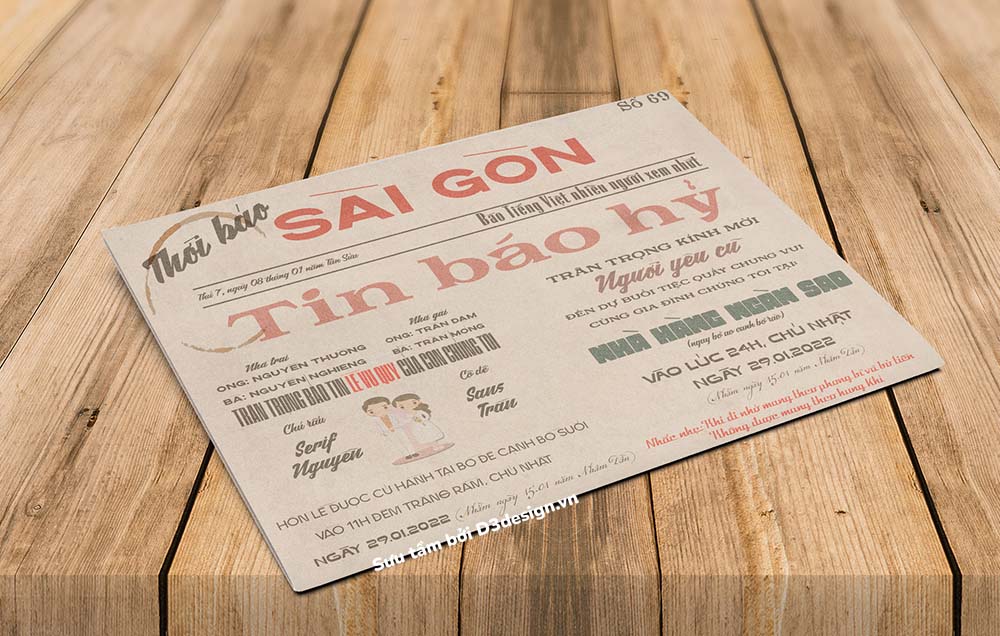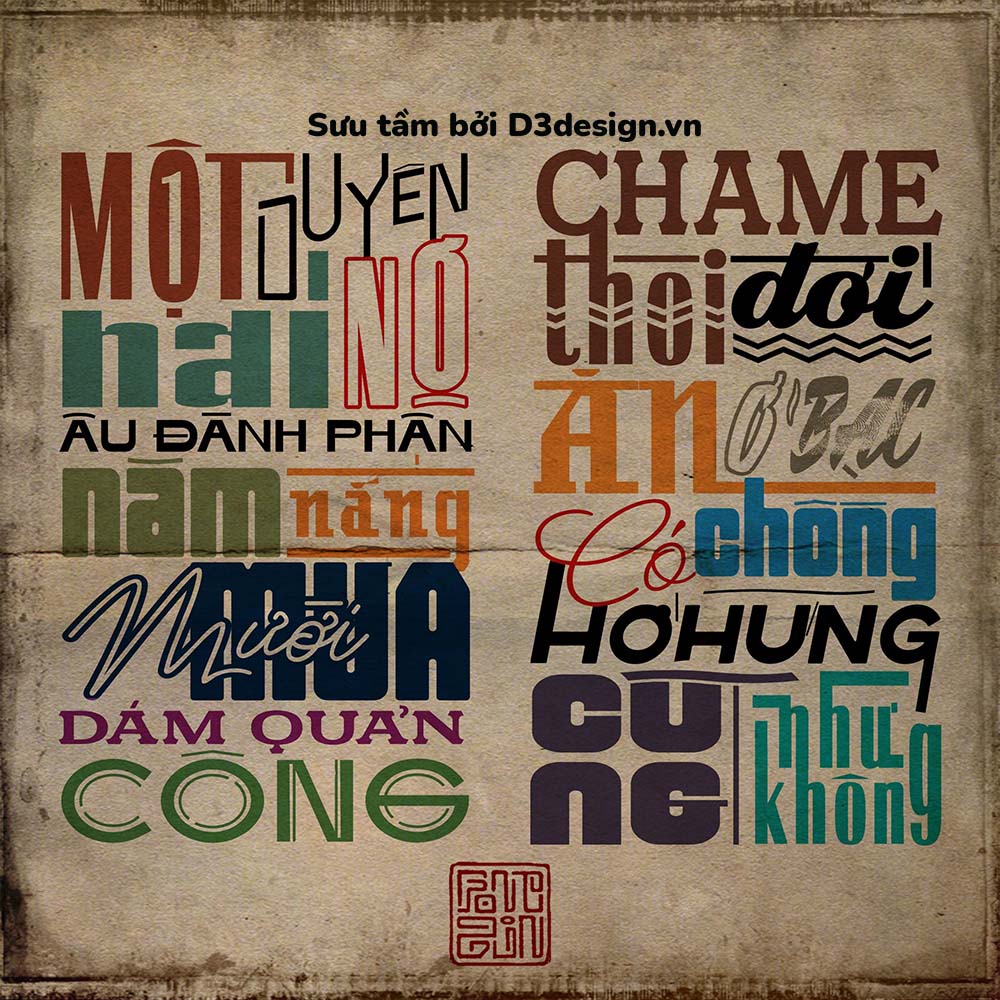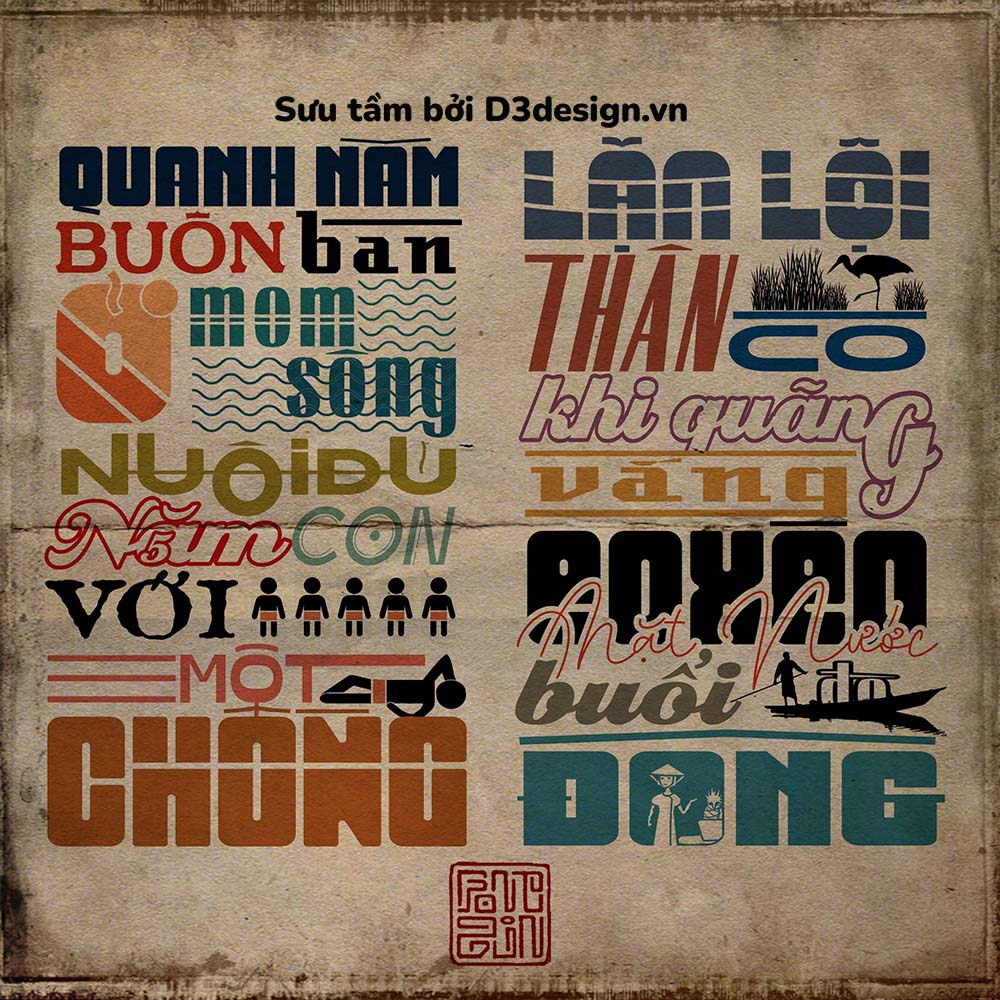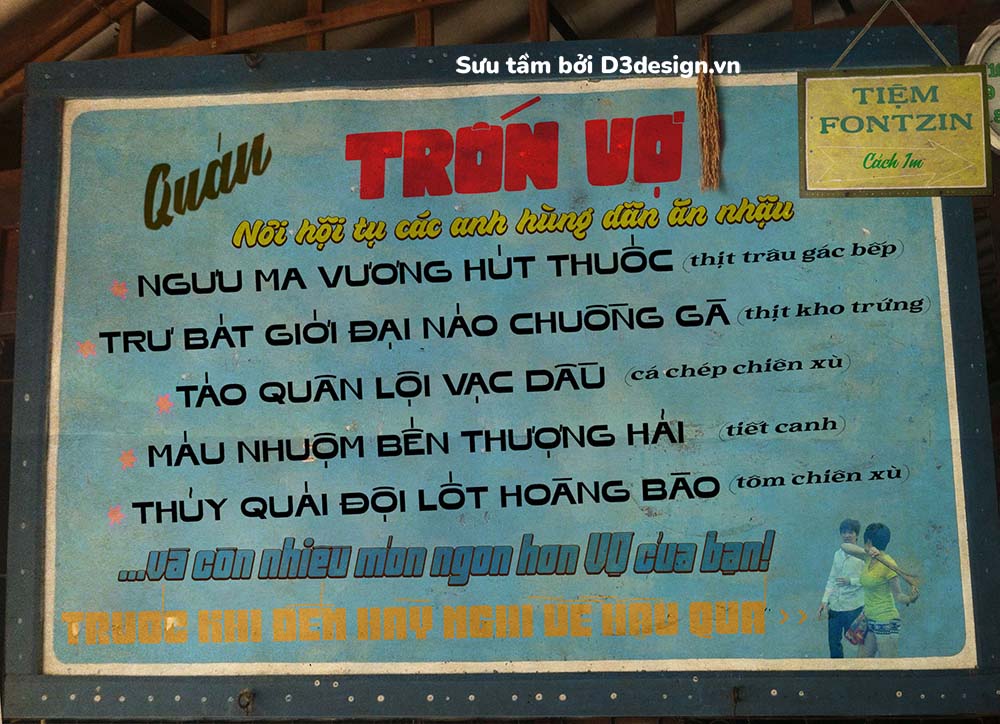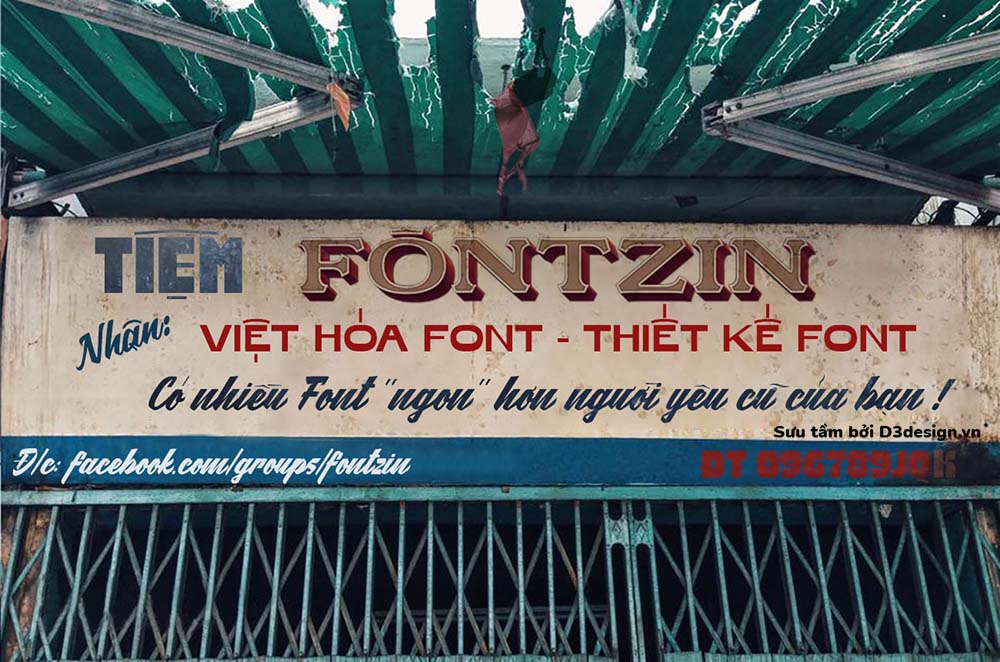
15 Font Việt Hóa Phong Cách Sài Gòn Xưa Cực Đẹp Cho Designer
Những Font này nằm trong dự án Font Sài Gòn xưa & nay do bạn Thái Hiếu hoàn thiện, bao gồm 20 Font Việt hóa.
Demo Font chỉ mang tính giải trí, vui vẻ. Một số demo mang hơi nhạy cảm & gây đau mắt. Hãy nhắm mắt để chiêm ngưỡng...